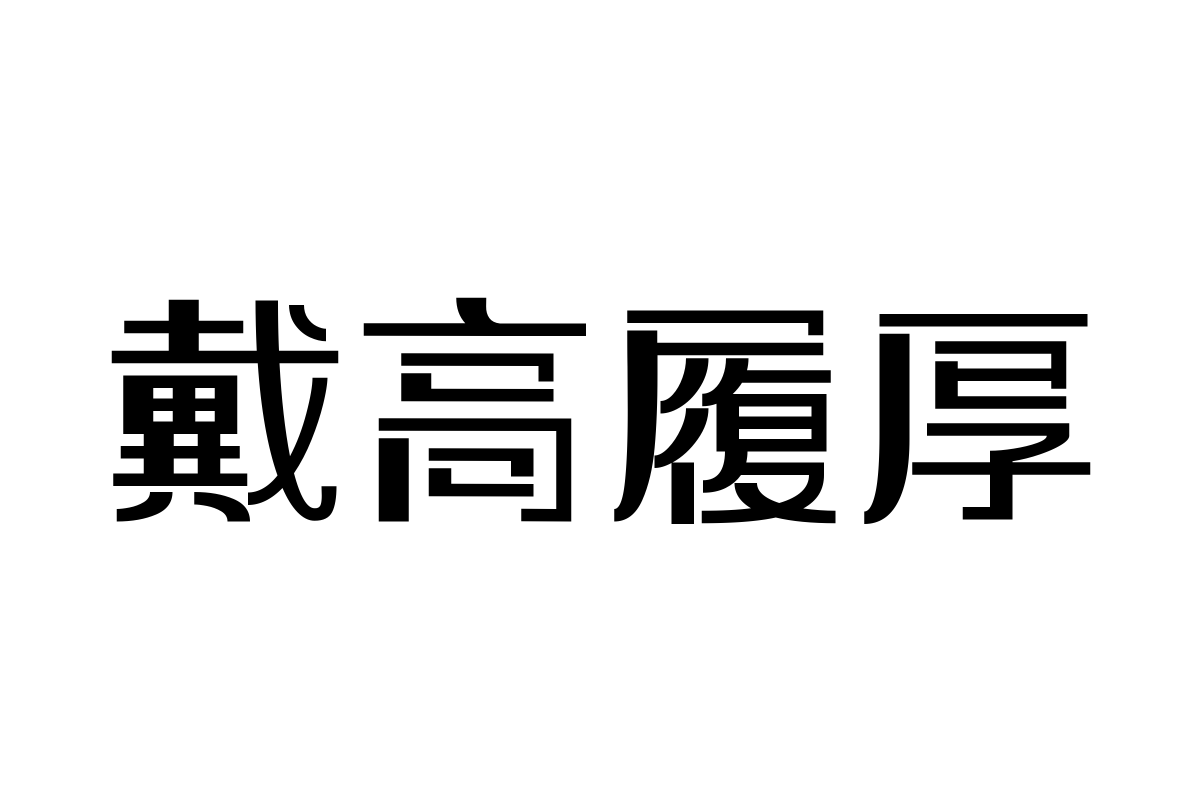
三极纵黑简体字体是一种具有特色的中文字体。它的设计灵感来源于传统的书法艺术,通过精细的笔触和流畅的线条展现出一种独特的美感。这种字体的特点是字形结构紧凑,笔画粗细适中,既有现代感又不失传统韵味。
三极纵黑简体字体适用于各种需要展示中文文字的场合,如书籍、杂志、广告、网页等。它能够很好地与各种背景色相搭配,使得文字更加突出,易于阅读。同时,这种字体也适合用于制作个性化的名片、海报等,为个人或企业增添一份独特的魅力。